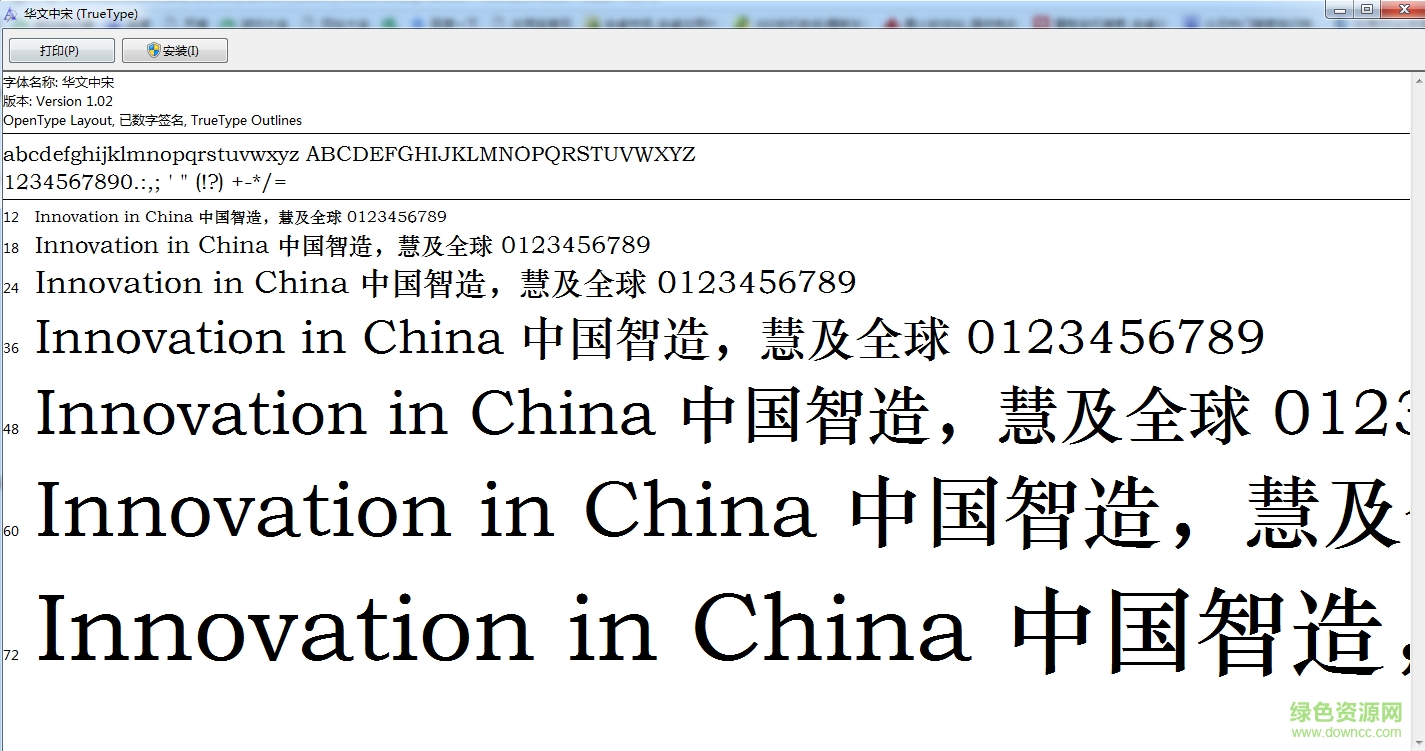
stzhongsong是什么字體?該字體又叫華文中宋是一款易讀性和欣賞性兼?zhèn)涞膐pentype格式版華文字體,字體形態(tài)質(zhì)樸,線條勾勒清楚,筆畫簡潔新穎,十分好看,歡迎大家免費下載!
stzhongsong字體介紹
華文中宋是是常用字體之一,在香港和臺灣地區(qū)叫做“明體”。華文中宋由宋體逐漸改變而來,但是跟宋體又有很大差異。華文中宋字體由歸國華人黃克儉先生開發(fā)與經(jīng)營,是由中國常州華文印刷新技術(shù)有限公司(SinoType)制作并持有版權(quán)的一種TrueType電腦字體,合作伙伴是Microsoft、IBM、Adobe等世界級巨頭。
stzhongsong華文中宋